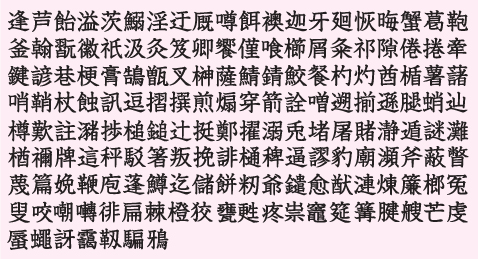
人名外字 1500V5 ビジネス版
本製品は、顧客名簿や住所録に最適な FEJN5ゴシック外字メイロウ外字(標準/太)明朝外字それぞれの書体の同等品を収録した3書体セットです。
読みで簡単入力できる「外字辞書」や、画数、部首、読みで検索できる「外字検索ツール」付き。
外字のみ収録しています。同梱のツールで「MS ゴシック」、「メイリオ」、「Meiryo UI」、「MS明朝」などにリンクをして使用します。
【外字収録数】1,637文字(人名外字1,470文字+「JIS X 0213-2004」で字形変更されたJIS第1・第2水準の167文字)